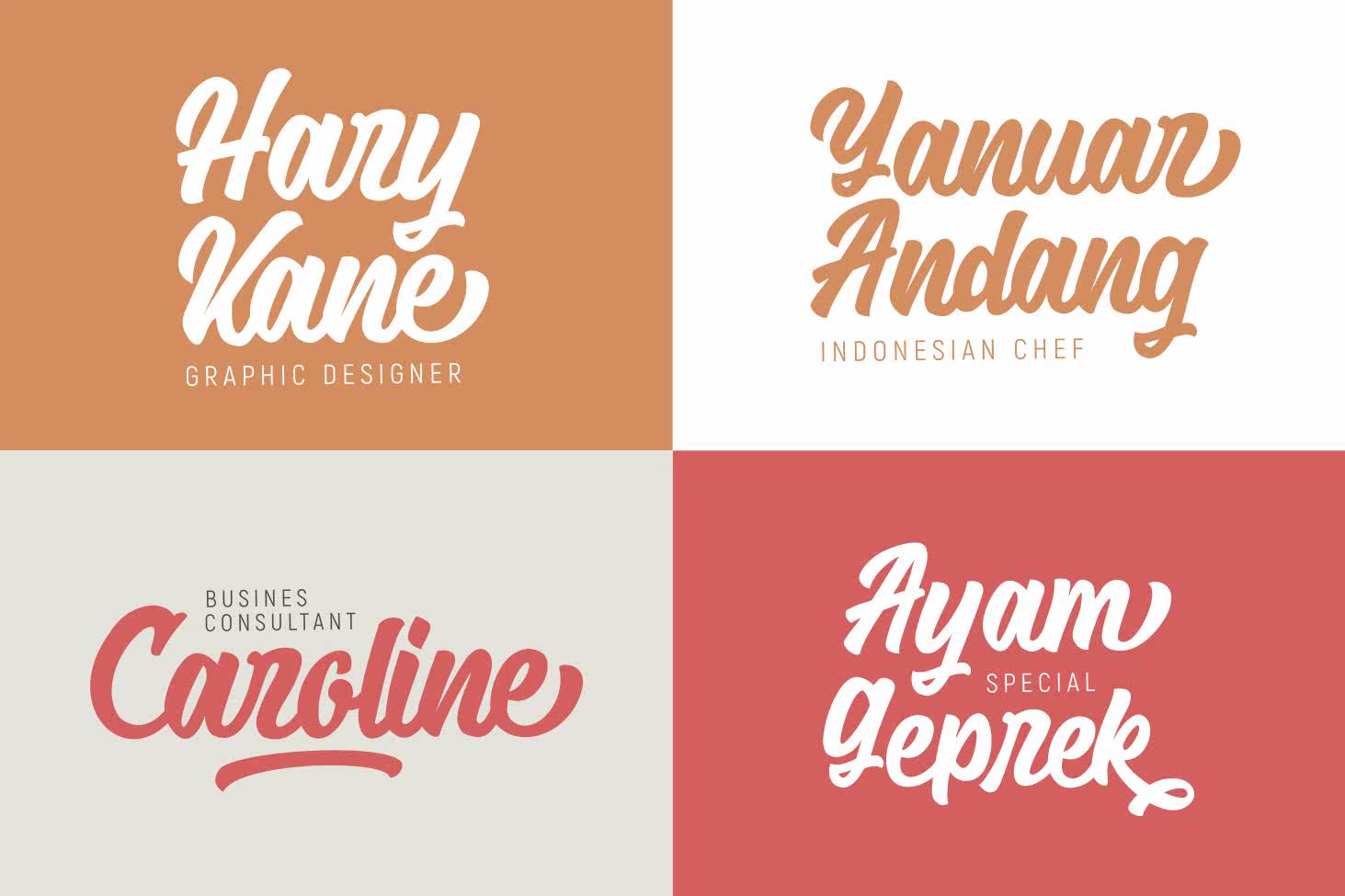
Hungryfont.IthasaBoldandSmoothStyle和Expectforming Any Designs Outstand.最适合品牌、包装、印刷标题、T恤设计、食品设计和类似项目。Hungryfont.IthasaBoldandSmoothStyle和Expectforming Any Designs Outstand.最适合品牌、包装、印刷标题、T恤设计、食品设计和类似项目。